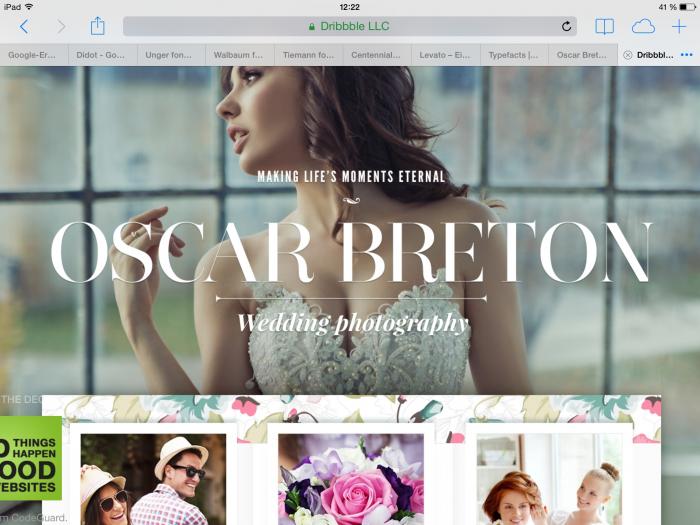
Ich suche die große Weiße Headline Schrift!
Ich bin mal die standard Schriften der Zeit Epoche durchgegangen:
Bodoni, Wallbaum, Didot, Kepler und viele weitere, aber leider schien mir die richtige nicht dabei zu sein!
Besonderes Merkmal der Schrift man achte auf die Verjüngung der Serifen des letzte Buchstabens, dieses Detail finde ich besonders markant.
Ich glaub um diese Schrift zu kennen muss man schon ein außerordentlicher Profi sein.
Wahnsinn, das ist Sie!
Hast Du das einfach gewusst oder wie bist Du fündig geworden?
Nur so als kleine zusätzliche Information: Die Narziss wird als eine der Schmuckschriften im Layout der Zeitschrift »Für Sie« verwendet.  :-)